艺术字体在线生成时需要根据不同字形和结构之间的结合和变化来加以改变,许多字体刚劲有力,而一些字体则刚柔并济,一些字体结构上显得匀称,而一些字体横平竖直,这便是艺术字的魅力,那么在艺术字体在线设计时有哪些技巧呢?
艺术字体在线设计可以关注现实的例子,看艺术字的笔画是否统一协调,假设:在标注的虚线内,横线笔画的设计变化、左上角、右下角修饰是否非常严谨,可以很清楚看其要表达的意图,许多艺术字都有圆角的笔画的改变,像红牛啤酒、加多宝凉茶,大多都有一个(或多个)笔画的间隔或者是切断,艺术字的笔画环境不一,但是设计修饰不可缺少。
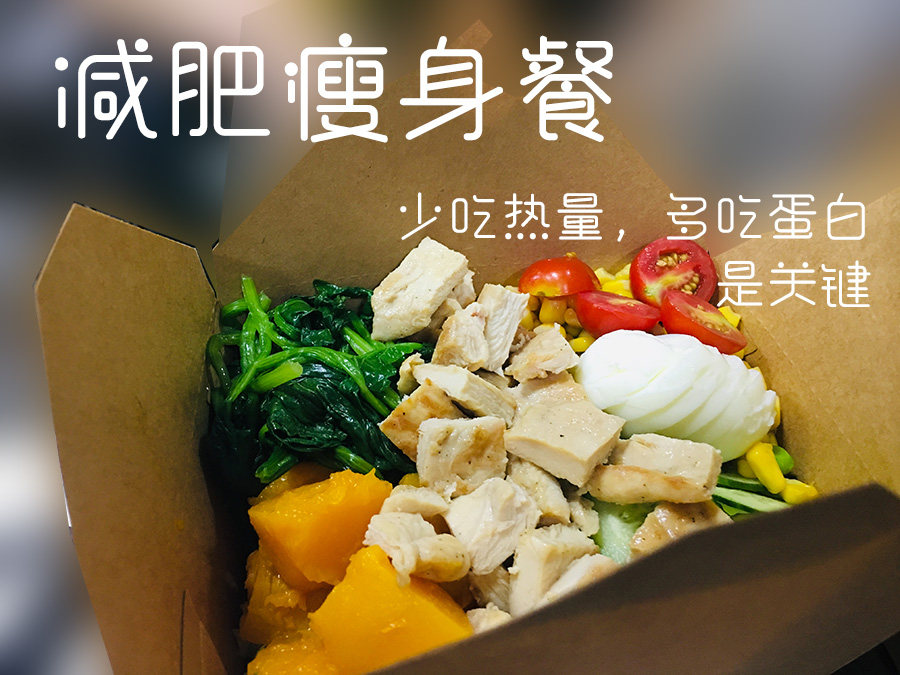
关于艺术字体的横竖粗细,是艺术字的直接感受,常用的艺术字体变形有长刀形或三角形,目前许多设计大师也将正方形和扁方形等引入其中。